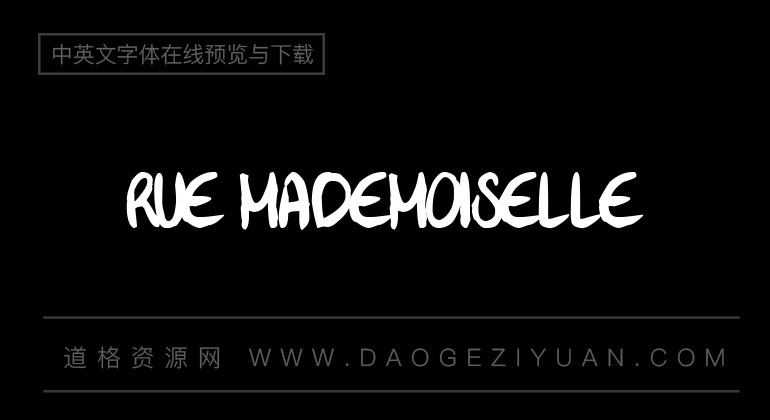
Rue Mademoiselle 是一款清新优雅的英文字体,由设计师Paula Nazal在2019年设计完成。它具有轻松、温柔、精致的风格,能够提供独特的视觉感受,是完美的选择用于报纸、杂志、广告、商标以及其他任何类型的文字设计。它的字形设计简洁、清新,字体里的每一个字母都充满着精致的细节,能够表达出精致和优雅的感觉。内容介绍
Rue Mademoiselle是一款非常不错的手写艺术字体,具有很好的视觉感,适合于文化类的宣传设计、商业类品牌的广告和产品包装设计以及个性化文字排版等较多场景。